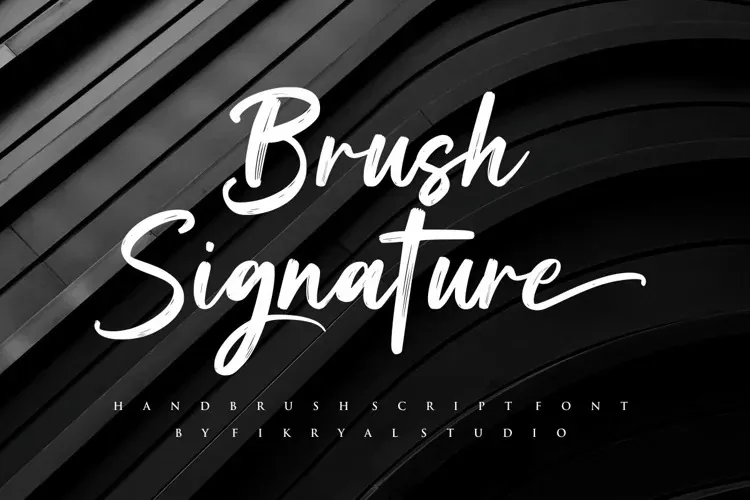
Brush Signature Font – Download Grátis
Essa fonte ‘Brush Signature Font’ é perfeita para designers que buscam uma combinação moderna e sofisticada. Ela foi criada pelo designer fikryal, mantendo um estilo orgânico e dinâmico. Este tipo de letra está disponível em um moderno design casual e forte, ideal tanto para uso em logotipos quanto para criações de marca, títulos, postagens nas redes sociais, anúncios, embalagens de produtos, etiquetas, fotografia, marcas digitais, publicações na web e muito mais. Seu formato fluido e natural faz dela uma opção versátil para todos os tipos de projetos design que exigem um toque atraente e elegante.